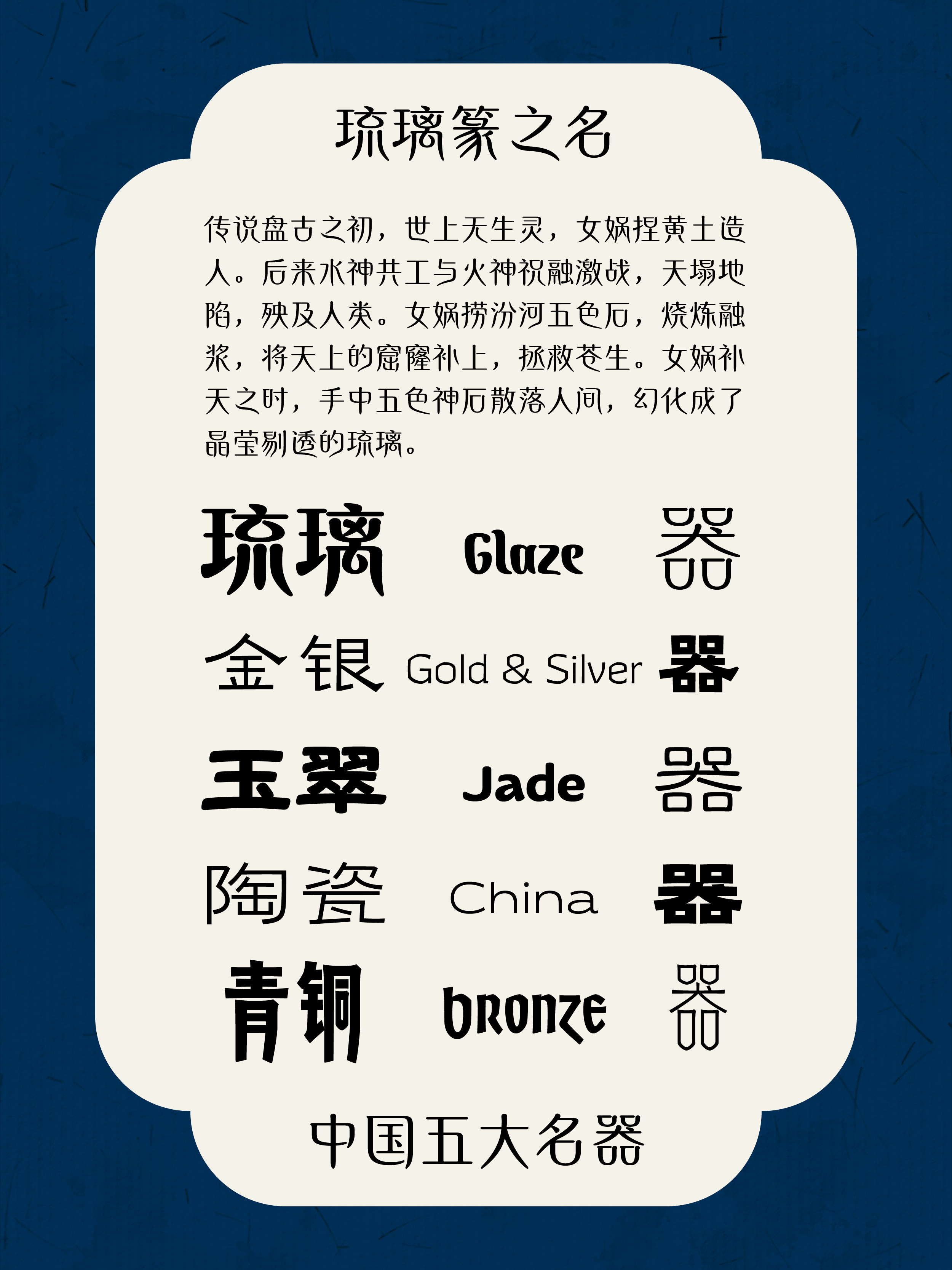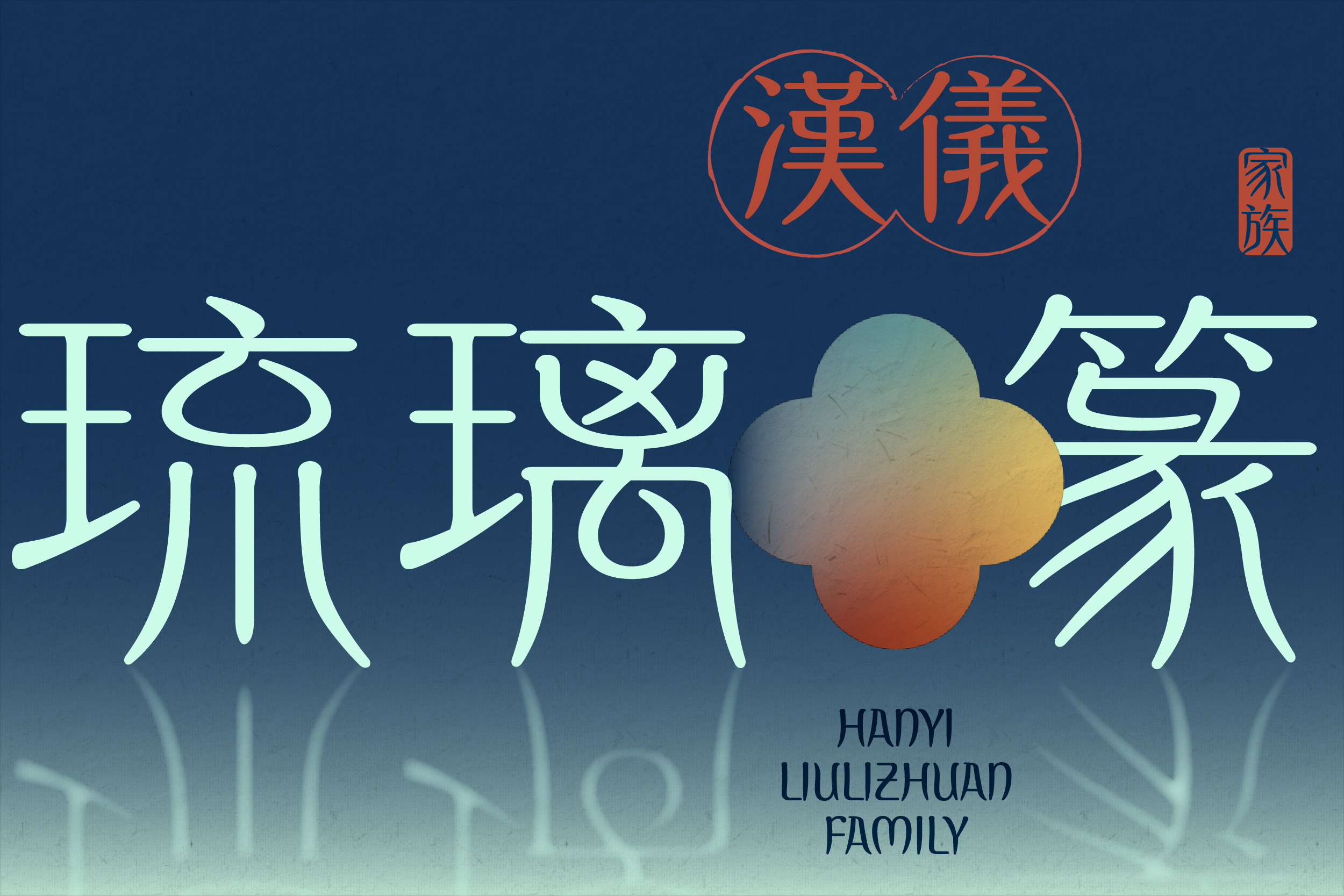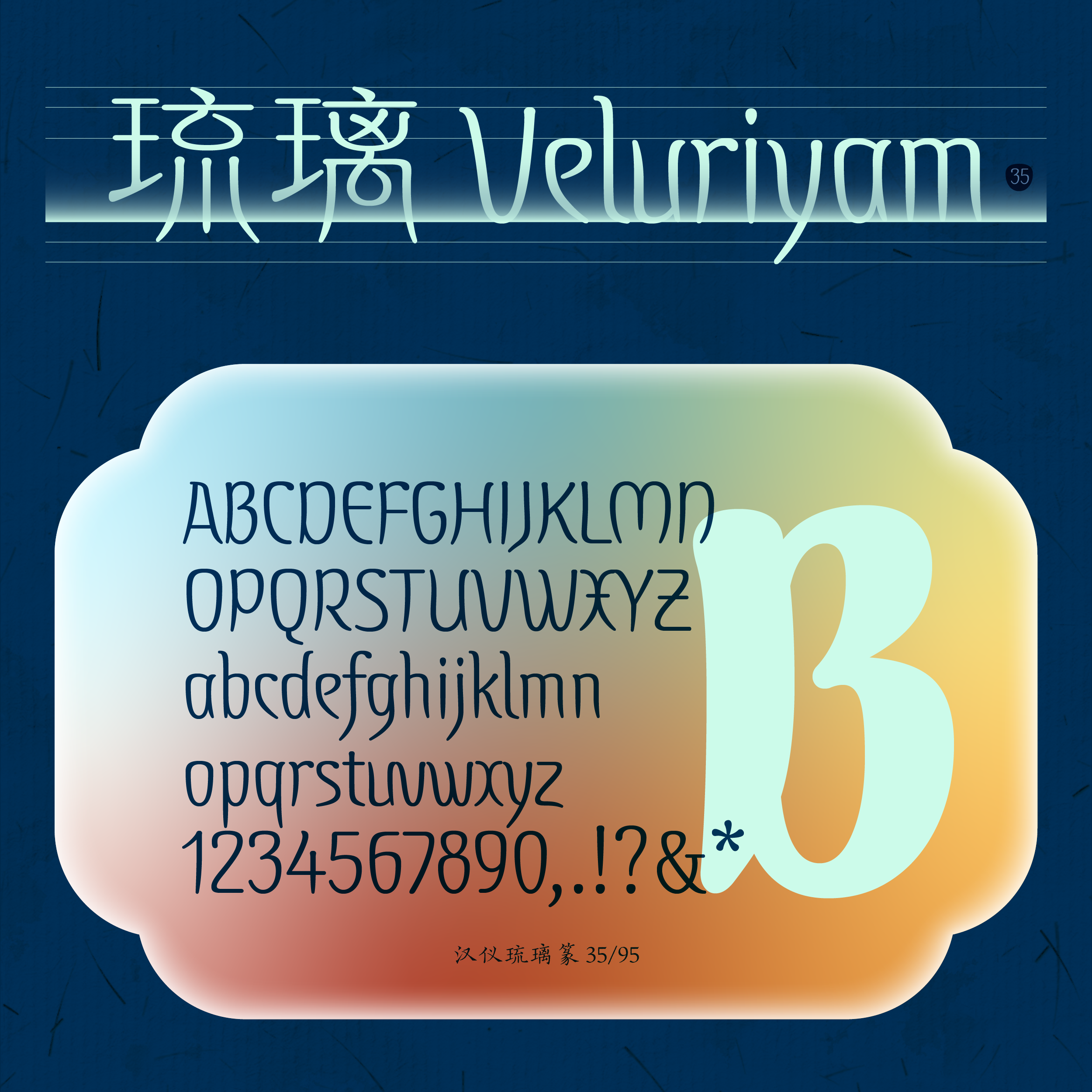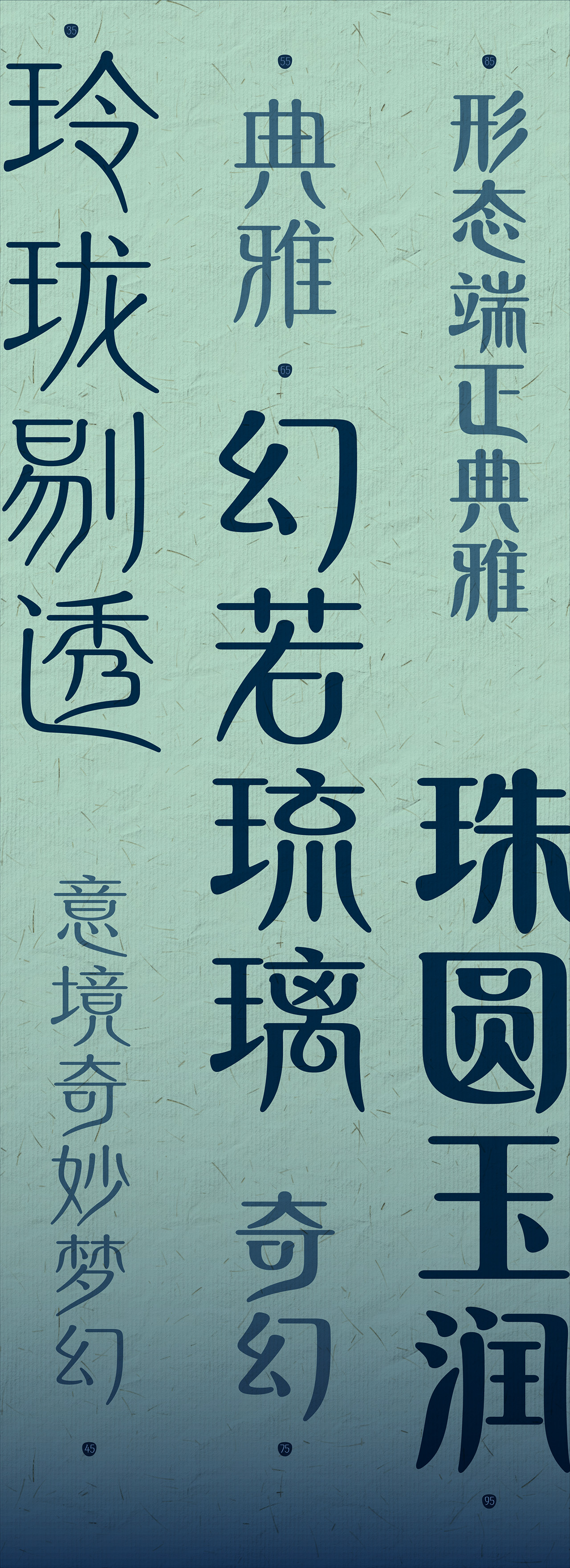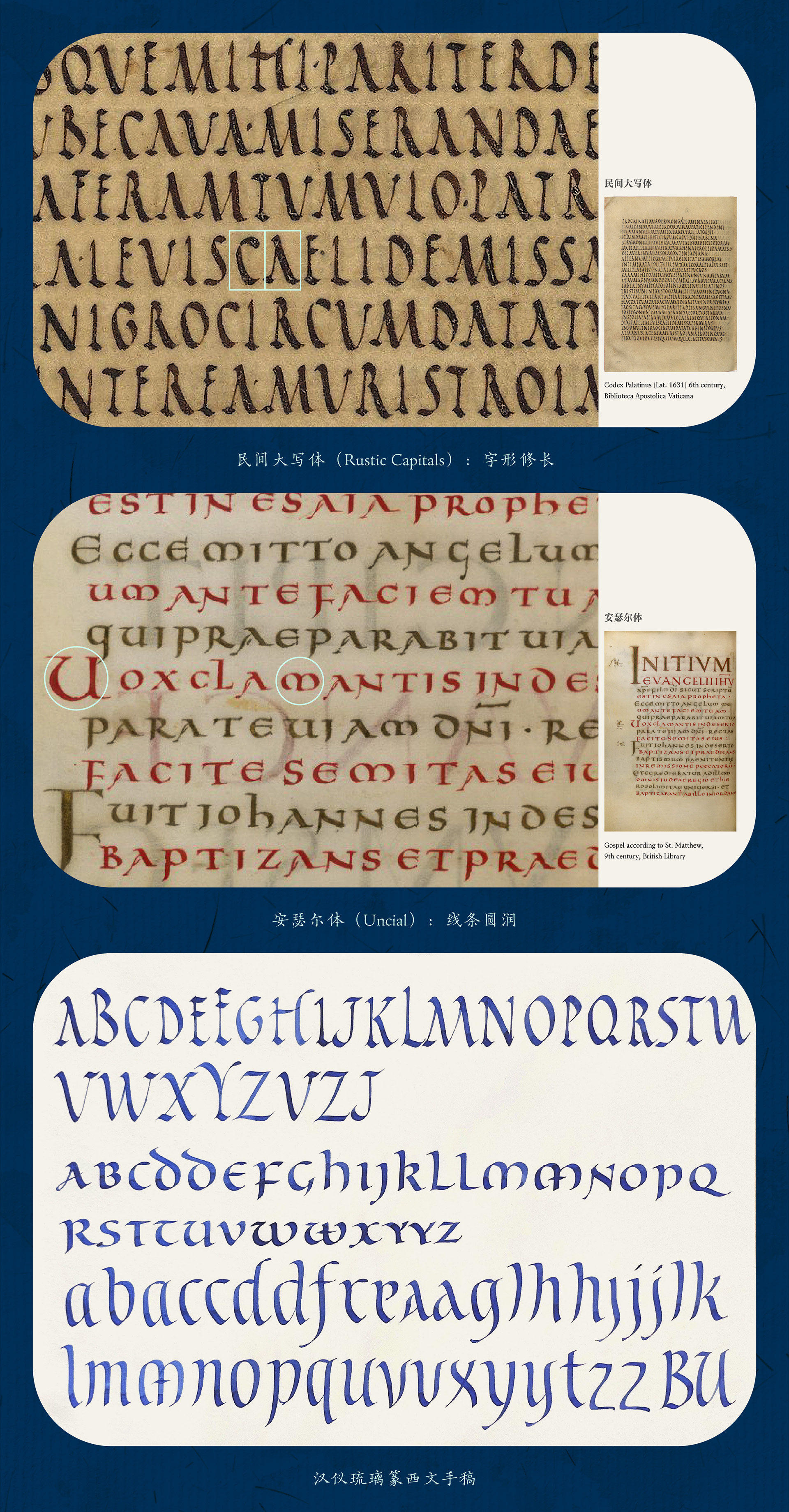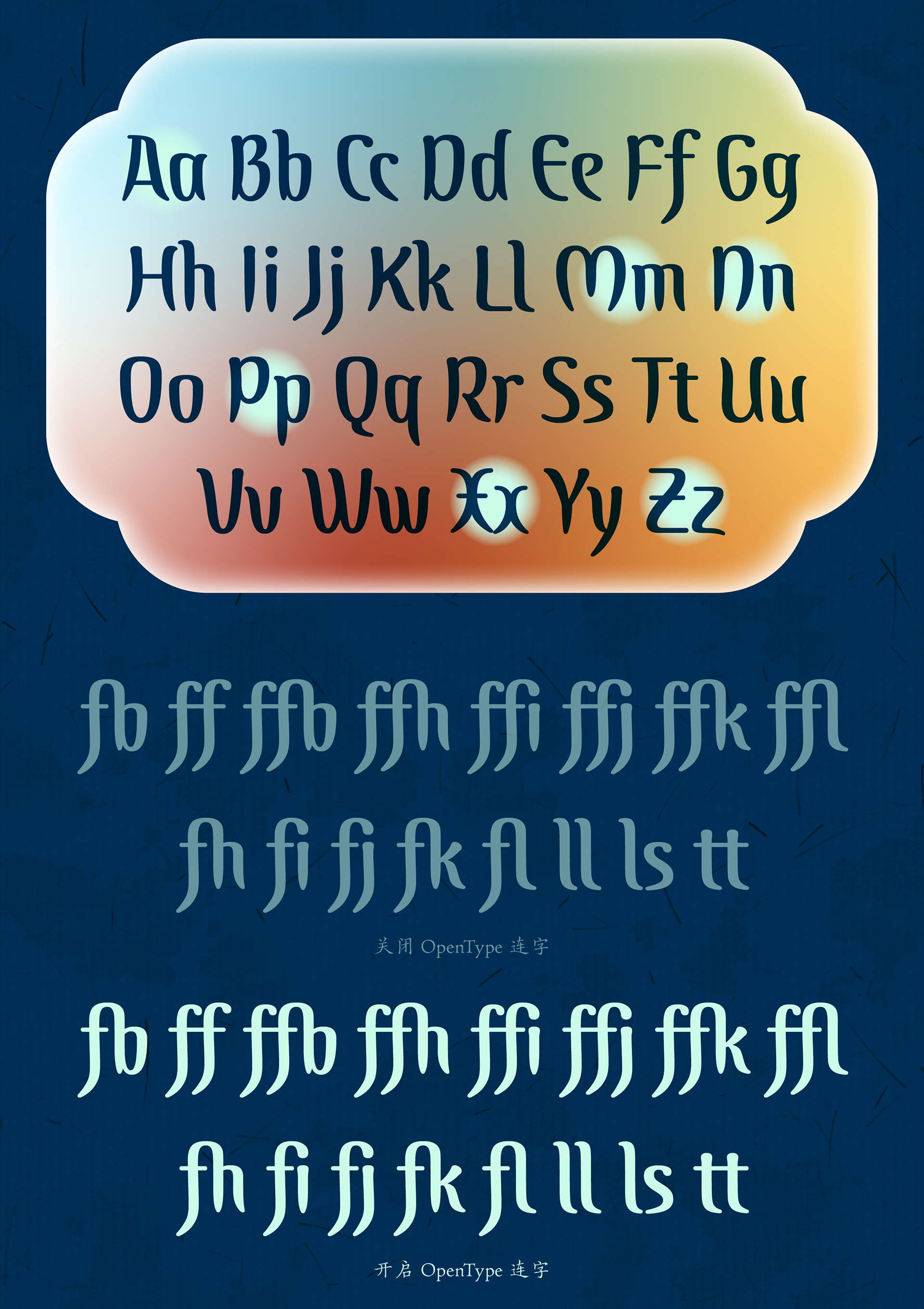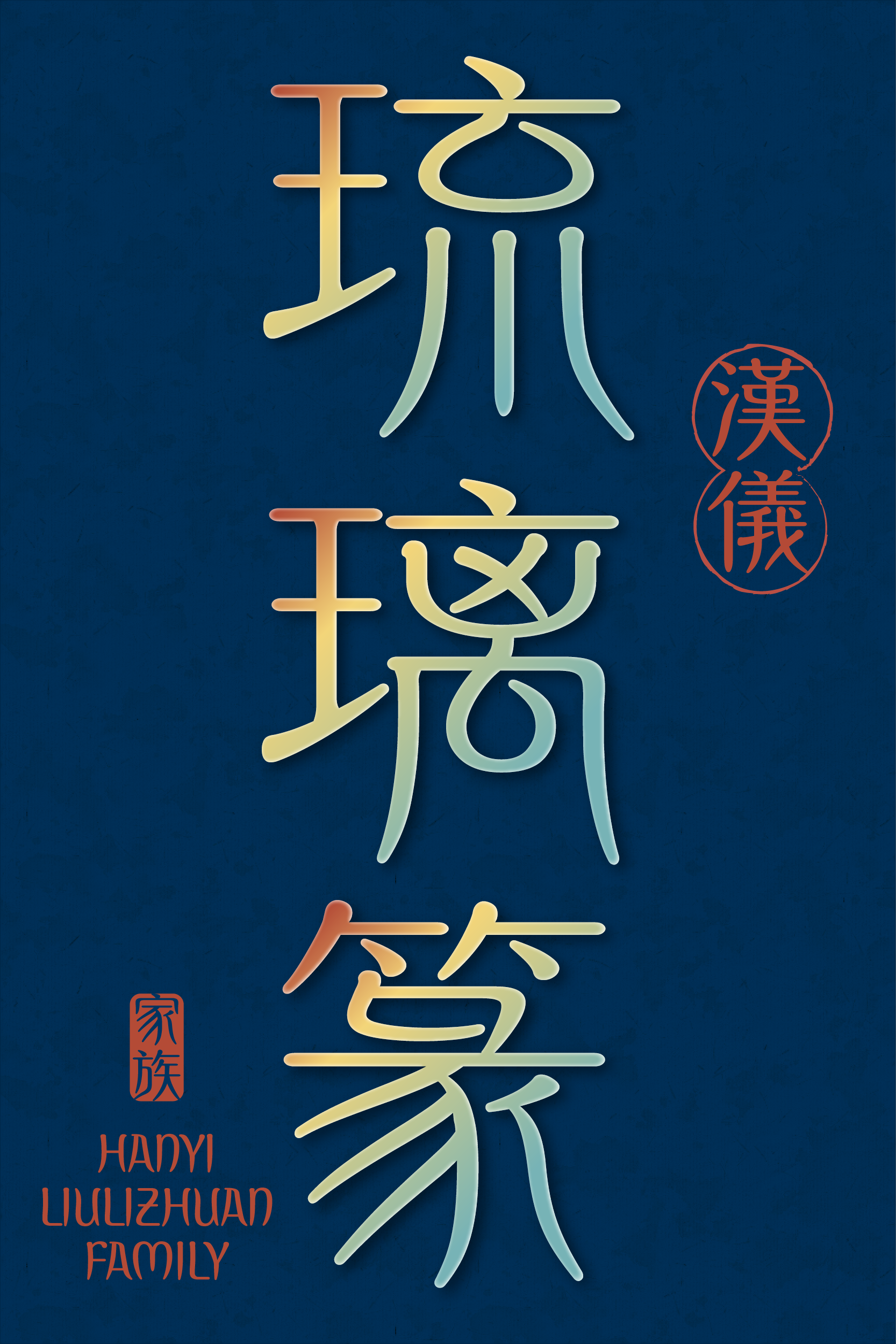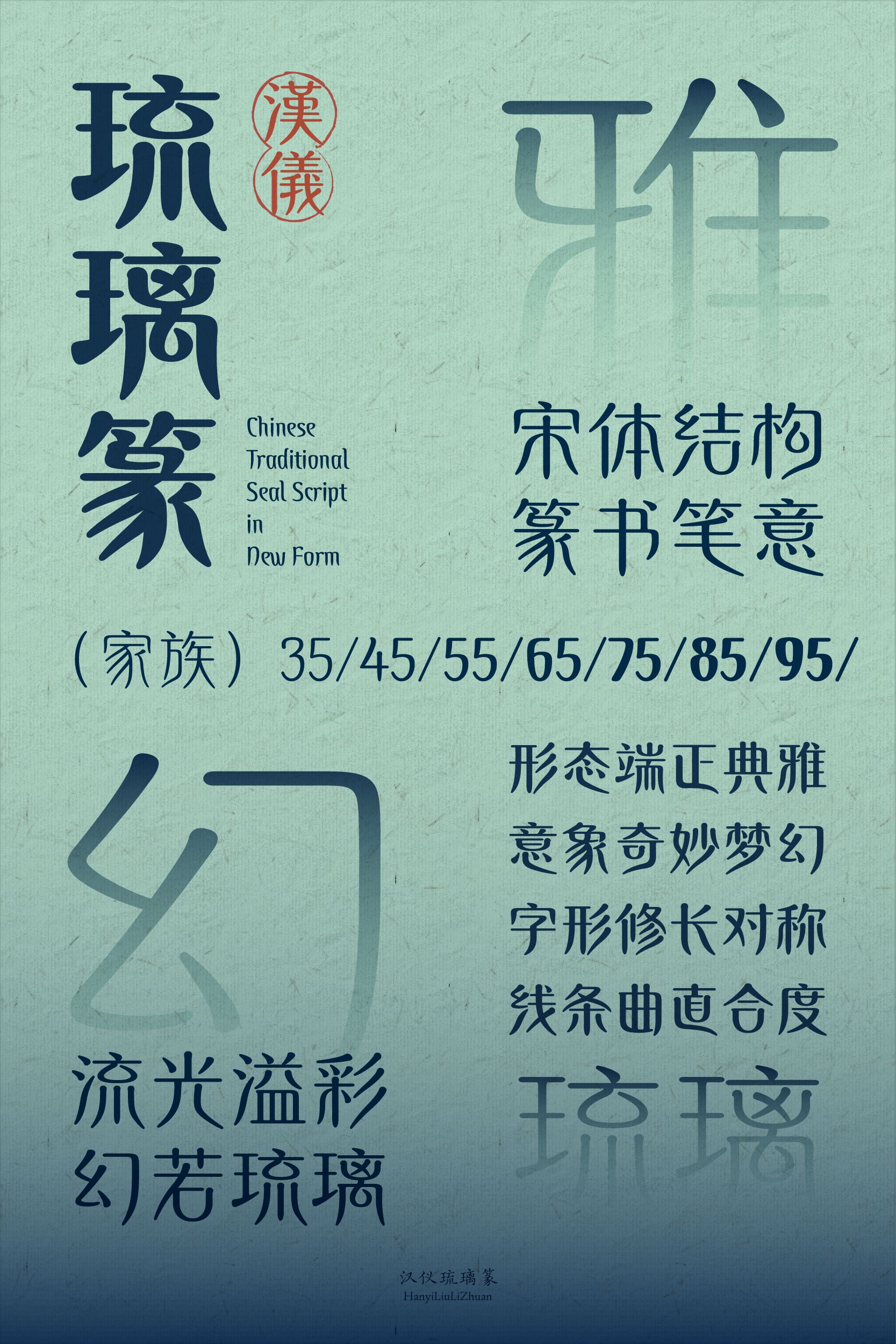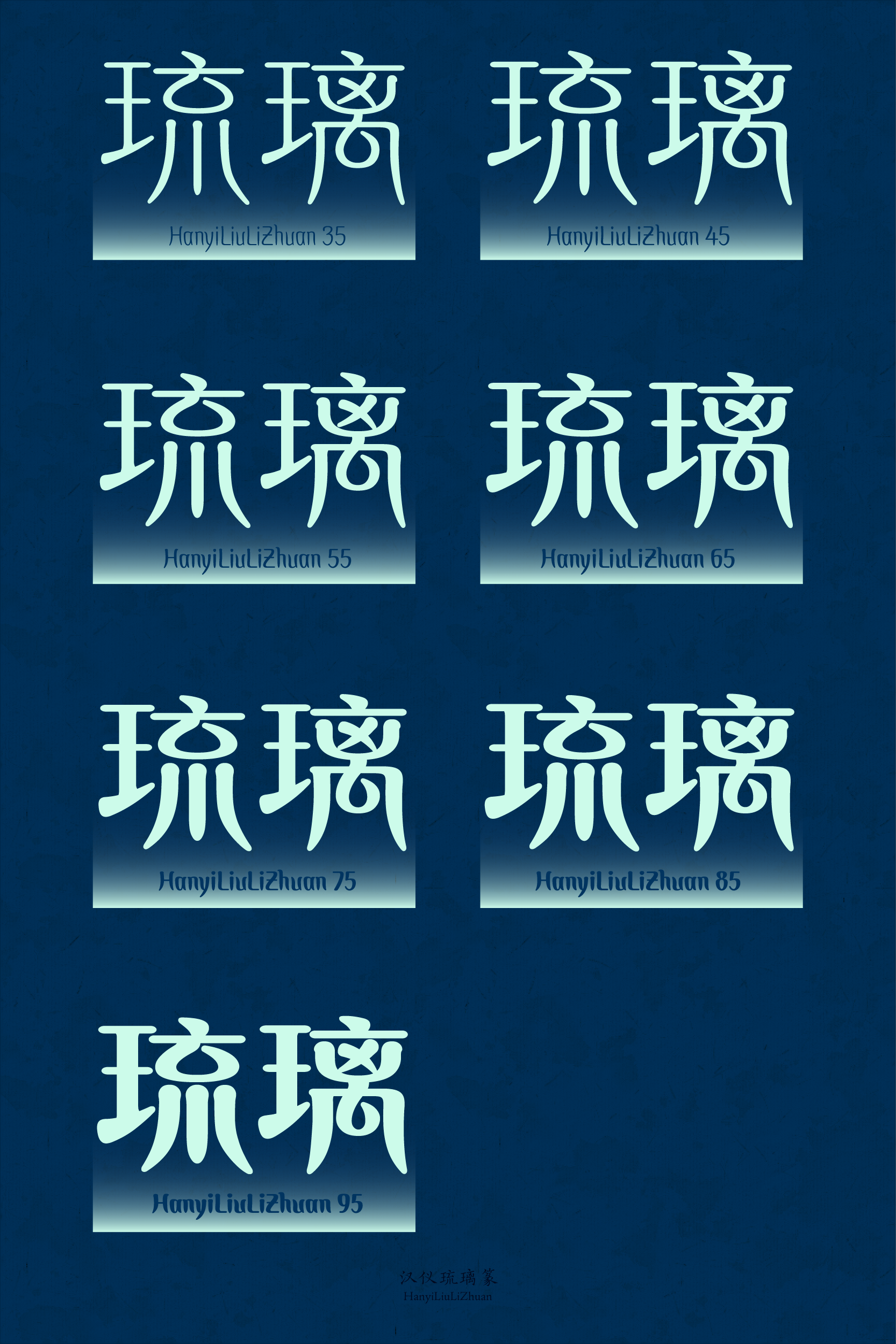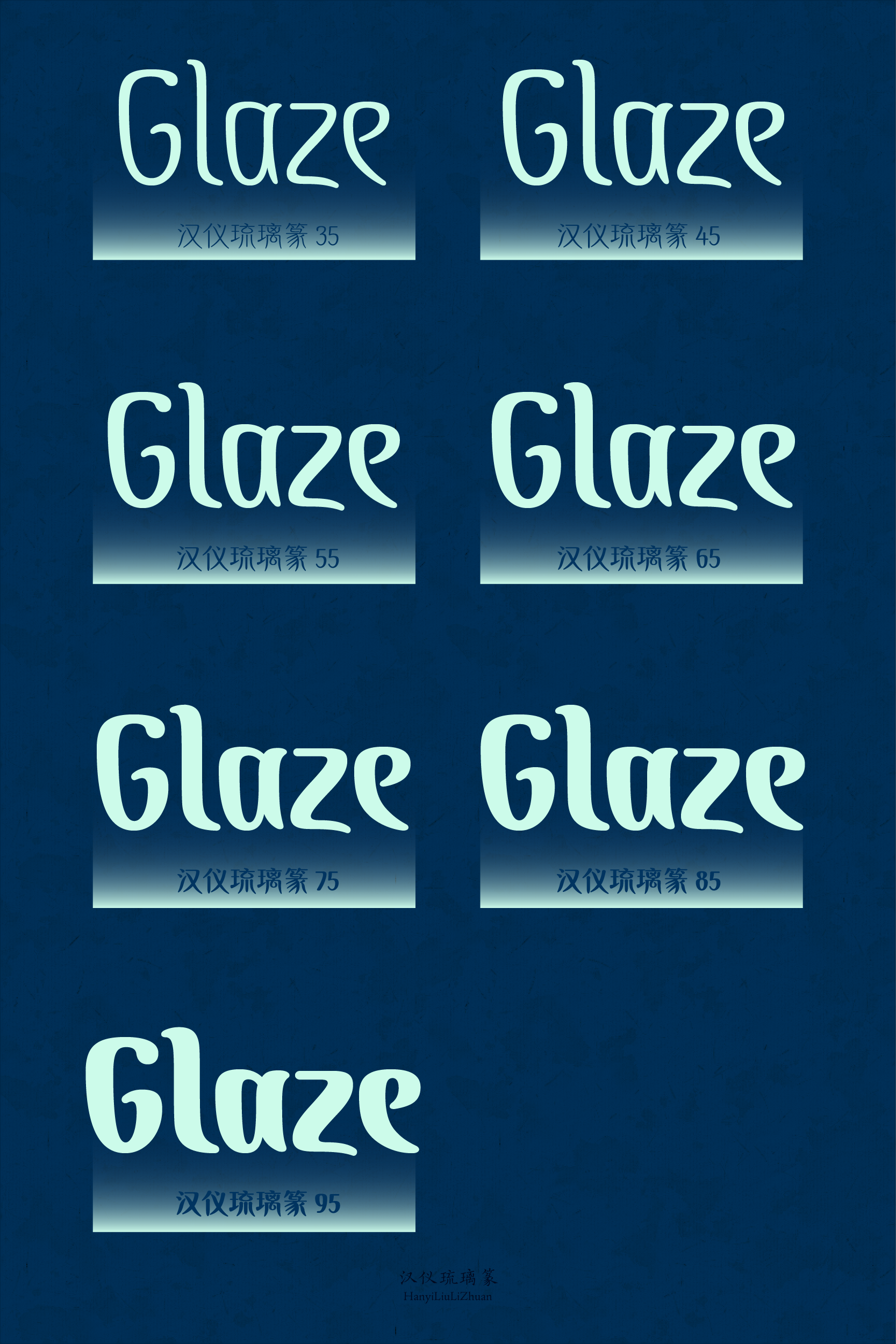
鎏光溢彩,幻若琉璃——汉仪琉璃篆
汉仪琉璃篆,幻若琉璃,形态端正典雅,意象奇妙梦幻。字形修长而对称,取宋体简洁清晰的结构与篆书婉转流动的笔意,为古老神秘的篆书赋予现代气质,古今交融。笔画线条曲直合度,动静相宜,流光溢彩。汉仪琉璃篆家族包含 7 个字重,细款玲珑剔透,粗款珠圆玉润,如同琉璃在光影之中变化万千。
汉仪琉璃篆家族推荐作为标题字体或短文本字体,姿态柔和优美,适宜中式风格的展览活动、书籍画册、服装配饰、美妆香氛等使用场景,更与传统手工技艺、文化艺术相称。
汉仪琉璃篆,端正对称,字形修长,线条婉转,幻若琉璃。
取宋体结构,简洁清晰;写篆书笔意,婉转流动。
横平竖直,曲线曼妙,曲直合度,动静相宜。
适当保留一些篆书的写法,更添神秘奇幻的色彩。
汉仪琉璃篆的西文保留了字形修长、线条圆润的特征,中西文传递出一致的视觉感受。
为匹配汉仪琉璃篆中文的书法来源,西文部分参考了民间大写体(Rustic Capitals)和安瑟尔体(Uncial)。
大写字母融合了民间大写体修长的字形和安瑟尔体圆润的线条,风格别致;小写字母则更注重字体识读的实用性,造型简洁。连字设计提供了更为流畅的阅读体验。
汉仪琉璃篆家族包含 7 个字重,细款玲珑剔透,粗款珠圆玉润,如同琉璃在光影之中变化万千。